「推し活」におすすめの日本語フリーフォント
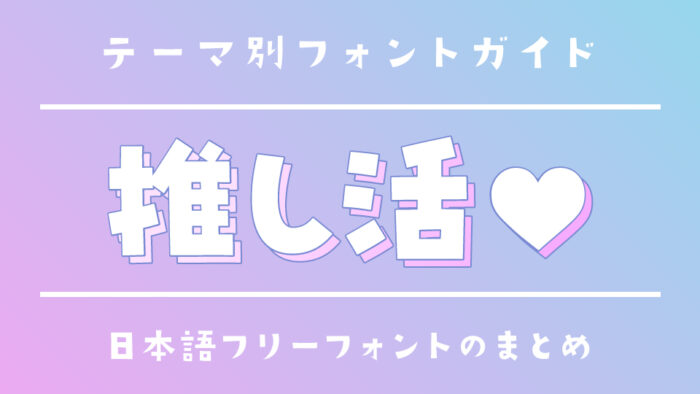
今回は、写真デコやうちわ、アクスタ台紙などの「推し活」にぴったりな日本語フリーフォントをご紹介します。
推しの名前をかわいく目立たせたい、メッセージをポップに届けたい――そんなときに大切なのがフォント選び。丸みのある愛され文字、キラキラ感のあるデコ系フォント、元気いっぱいの手書き風など、“推し”への愛を全力で伝えられるフォントが、推し活には欠かせません。
今回は、ファンサボード、SNS投稿、チェキ加工など、あらゆるシーンで使える推し活向け日本語フリーフォントをピックアップしました。自分の「好き」をとびきり可愛く表現したい方は、ぜひ参考にしてみてください!
「推し活」に絶対使いたい!日本語フリーフォントまとめ
以下の画像は本記事で紹介している一部ですが、推し活にぴったりな目立つフォントを中心にピックアップしてみました。
にくまる
にくまるフォントは、まるまるっとぷっくらしているフォルムは愛らしく可愛らしいデザインになっています。
太さもあるので、応援うちわなどに使うとインパクトあること間違いなし!応援うちわで利用されている方が多い人気あるフォントの1つです。
ポプらむ☆キウイ
ポプらむキュートフォントは、少女向けマンガなどに使われていそうな丸みがある可愛くポップな文字になっています。
文字のバランスに遊びがあり、文字ごとに個性が感じられるので、明るくにぎやかな雰囲気を作りたい「推し活」シーンにぴったりです。
推しゴフォントは、推し活用グッズ制作用として作られたフォントです。指ハートなど推し活で使えるアイコンが35種類使うこともできる可愛いフォントです♡
親しみやすく愛される形でありながら、太さもしっかりあるので視認性が高く、名前を目立たせたい「推し活」にぴったりです。
大大大大だぁい好き
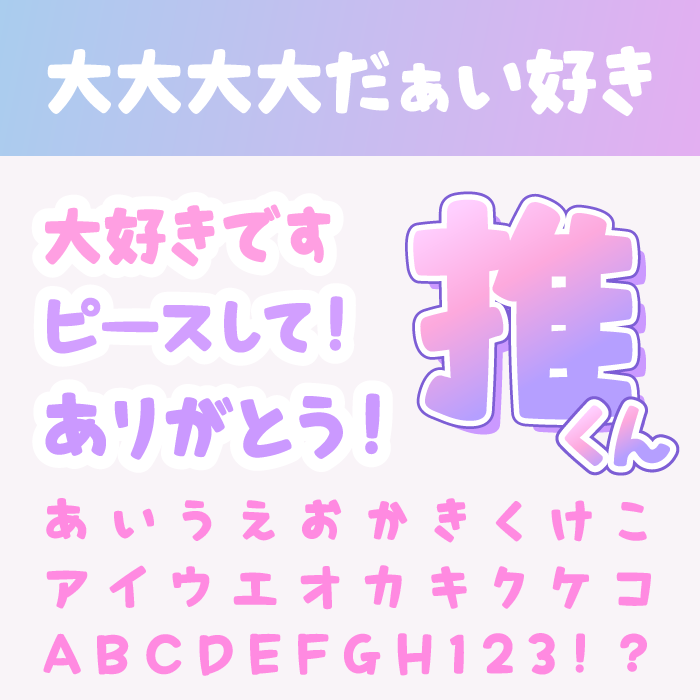
大大大大だぁい好きフォントは、手書きの勢いとゆるさをそのまま活かした、賑やかで元気いっぱいの可愛いデザインフォントです。
トガリテ
トガリテフォントは、文字にトゲが生えているようなデザインが特長のフォントです。
推しの「かっこよさ」や「儚さ」を表現したいときにぴったりのフォントです。女性向けのビジュアルや、ファンタジー系・アイドル系のデザインにも映える仕上がりです。
あおさぎ
あおさぎは、伝統的な明朝体のやわらかいエッセンスを残しつつ、全体的に軽やかで親しみやすい印象のあるフォントです。
文字の縦長シルエットと細めの線で構成されており、清楚で爽やかな雰囲気を醸し出しています。崩しすぎず固くなりすぎない文字を探している方におすすめです。
きょうりゅうグラタン
きょうりゅうグラタンは、とにかく太く、ユニークな形をしているので親しみのあるフォルム。ほっこりするような優しいデザインはオタ活グッツ制作にぴったりなフォントです。
ポップでフラットな表情は、推しの名前を目立たせたい場面や、グッズのデザインなどにも相性良く使える万能さを持ったフォントです。
クラフト明朝
クラフト明朝は、手書き文字らしいかすれている加工がされている可愛らしフォントです。
明朝体の品の良さを残しながらも、やわらかい線の太さや角の表現が親しみやすく、控えめながらも可愛らしい雰囲気を持っています。推しへの感謝や手紙風のデザインにもマッチする、温かみのあるフォントです。
けいふぉんと
けいフォントは、オタ活グッツやオタ活動画制作などさまざまなシーンおいて定番で、人気のあるフォントです。
文字もちょうどよい太さで読みやすく、少し動きがあるので可愛らしい、そのため使いやすいフォントです。
ラノベPOP
ラノベPOPフォントは、ライトノベル風のポップで親しみやすいデザインに、ふっくらしたフォルムが合わさった、見出し映えするフォントです。
アニメやアイドル、VTuberなどとの相性も抜群で、推し活のテンション感をしっかり支えてくれるフォントです。
コーポレート・ロゴ(ラウンド)
コーポレート・ロゴ丸フォントは、柔らかな曲線と均整の取れた文字組みが特徴的な、シンプルながら存在感のあるフォントです。
角丸なのですが、可愛くなりすぎずに固くなりすぎずな印象のフォントです。少し横に縮んでいる文字なので、グッツに文字数を長めに入れたいなどにも向いています◎
鳩とブリキのワンダランド
ころんと丸みを帯びたシルエットに、どこか懐かしさのあるバランス感が可愛らしいフォントです。
素直で愛嬌のあるラインが印象的で、にぎやかすぎず整った見た目なので、ライブグッズやうちわ文字にもぴったり。太くはっきりとした文字なので遠くからでも読みやすく、推しへのメッセージにしっかり想いを込められるフォントです。
ニコ角
ニコ角フォントは、カクカクとしたシルエットに個性がにじむ、やんちゃで可愛い雰囲気のあるフォントです。
デフォルメされたような平仮名の形や、コンパクトにまとまった造形が特徴で、文字を並べたときのリズム感が面白い仕上がりになるフォントです。
めもわーる
ニコ角フォントは、ぎゅっと尻窄みなフォルムに手書きのような柔らかさのある丸みによって、やさしい気持ちを表現できるフォントです。
大きな文字でも小さな文字でも読みやすく、うちわ文字や応援メッセージなど幅広い用途に活用できる万能タイプのフォントです。
横浜ドット
横浜ドットフォントは、ドット絵風のデザインが特徴的な、Y2Kな雰囲気のフォントです。
ピクセルで描いたような形状はインパクトがあり、ライブネームボードやSNS用画像などでもパッと見で目を引くデザインです。キャッチーで楽しいムードを演出できるので、ポップカルチャー好きな方の推し活にもぴったりです。
モッチーポップ
モッチーポップフォントは、もちもちとした丸みと、絶妙な太さのバランスが楽しいポップ感を生むフォントです。
どの文字にも愛嬌があり、揃えて並べると楽しげでキュートな印象になります。グラデーションや縁取りとの相性も良く、推しへの愛をデコレーションして伝えたいときにぴったりなフォントです。
けいなんポップ体
けいなんポップ体は、親しみやすくポップな造形の中に、手描き風の揺らぎが可愛らしく溶け込んだフォントです。
丸みと角張りを両立したユニークな形状で、並べた文字にほどよいリズム感のあるフォントです。
源暎きわみゴ
源暁きわみゴは、直線的なゴシックの骨格にパワフルさとポップ感を加えた、存在感あるフォントです。
文字の強さがありながら、太すぎず重すぎないバランスで構成されているため、硬派になりすぎず可愛さも演出できます。目立たせたい推しの名前や決めフレーズに最適な、使い勝手の良い1本です。
くらむぼん
くらむぼんは、平仮名・カタカナともに均整のとれたやや太めのデザインで、安定感と可愛らしさをあわせ持つフォントです。
どっしりした印象ながら、角のとれたやさしいカーブが全体を柔らかく包み込み、子どもっぽすぎない大人可愛い印象も兼ね備えています。